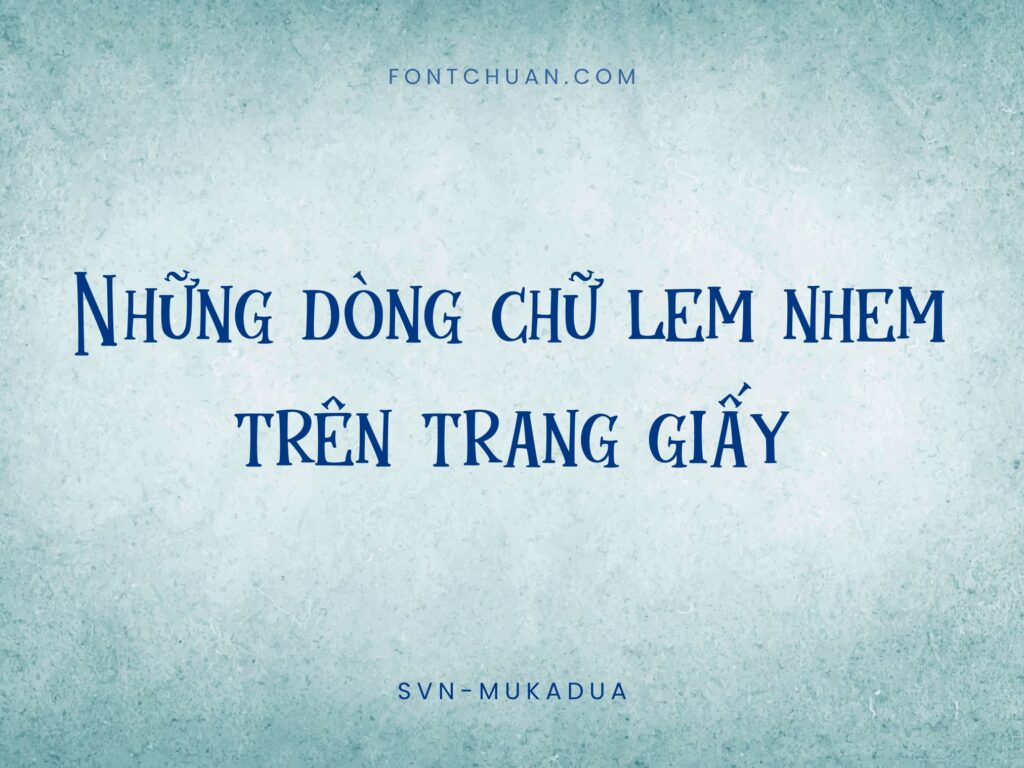
Font SVN Mukadua Việt Hóa
Tác giả Font: Letterhend
Font SVN Mukadua là phiên bản Việt hóa của kiểu chữ Mukadua, được thực hiện bởi STYLEno.1 Fonts. Mukadua là một bộ đôi font chữ bao gồm hai phong cách: serif và script, được thiết kế bởi Letterhend Studio. Tên gọi “Mukadua” mang ý nghĩa “hai mặt”, thể hiện sự linh hoạt của font trong việc sử dụng cho cả các thiết kế vui tươi, thân thiện lẫn các chủ đề tối, kinh dị hoặc bí ẩn. Phiên bản serif của font mang một số yếu tố Font Gothic, với các đường nét góc cạnh và mạnh mẽ, tạo thêm cảm giác cổ điển, bí ẩn cho các thiết kế. Font bao gồm các ký tự chữ hoa, chữ thường, dấu câu, chữ số và hỗ trợ đa ngôn ngữ. Ngoài ra, font còn cung cấp các tính năng OpenType như các ký tự thay thế theo phong cách và ligatures. Font này phù hợp cho nhiều mục đích sử dụng khác nhau như thiết kế logo, tiêu đề, bao bì sản phẩm và các ấn phẩm truyền thông.
SVN Mukadua lý tưởng cho các dự án thiết kế yêu cầu sự linh hoạt và độc đáo, như thiết kế logo, tiêu đề, bao bì sản phẩm và các ấn phẩm truyền thông. Các ngành nghề như quảng cáo, giáo dục và thiệp cưới có thể tận dụng font này để tạo điểm nhấn trong thiết kế. Ngoài ra, font cũng thích hợp cho các sự kiện như Halloween, Tết, Giáng sinh và các lễ hội khác.